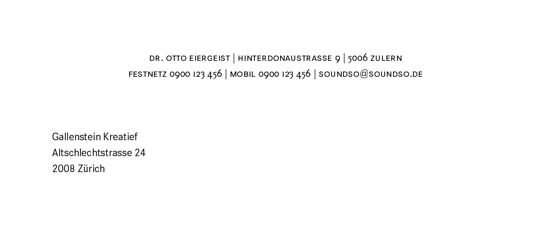
Bewerbungsschreiben für Polygraf
Hallo Miteinander!
Ich bin dabei ein Bewerbungsschreiben für eine stelle als Polygrafen aufzusetzen. Da dieser Beruf ja sehr stark mit der Schrift und die Anwendung in der Praxis verwandt ist, würde ich gerne wissen ob es irgendwelche Aspekte zu berücksichtigen gibt... ? Ich habe mir vorgestellt, dass sicher einmal die Lesbarkeit (Schriftgrad, Abstand, Zeilenlänge etc.) eine Rolle spielt und auch ein schöner Flattersatz gut ankommen wird.
Das ist jedoch nur meine Meinung als Frischling. Hat jemand damit Erfahrung oder Erfahrung mit Bewerbungsschreiben generell und könnte mir weiter helfen?
Bei der Schriftwahl bin ich mir auch noch nicht ganz sicher ob es eher eine Grotesk oder Antiqua sein sollte.
Für jegliche Hilfe wäre ich wirklich überaus dankbar!
Lieber Gruss Patrick
Hallo RobertMicheal,
Schriften hätte ich viele zur Auswahl. Da ich aber davon ausgehe, dass diejenigen, die die Bewerbungen unter die Lupe nehmen, eher mit einer alltäglichen Schrift wie z.B. der Garamond, Times New Roman oder Arial anzusprechen sind, als irgend einer Schrift aus dem Internet mit wildem stil (übertriebenes Beispiel).
also ich würde mich freuen keine systemfonts in einer bewerbung
lesen zu müssen. wenn dann höchstens georgia. ich wirds mit einer
office-schrift versuchen. fago office zum beispiel.
Ist ein Polygraf nicht ein Lügendetektor?
Ja. Es gilt aber auch Typograf+Lithograf=Polygraf 8)
Aber genau! ;)
@ RobertMichael; könntest du dir mal mein Schreiben ansehen? Ich habe es als PDF hier hochgeladen:
Die Angaben sind ein wenig verfälscht um mein Gesicht zu wahren :lol:
Wie findest du es? Für den Haupttext habe ich eine FagoCo medium benutzt und für die Überschrift eine FagoNoLF Bold. Jetzt weiss ich nicht, ob man diese, eigentlich, verschiedenen Schrifttypen in einem Brief gleich enttarnen kann oder ob ich es so durchgehen lassen kann.
Bei der Satzanordnung bin ich mir auch noch nicht sicher. Ich habe die Laufweite und den Zeilenabstand vergrössert damit es leichter zu lesen ist (war anfangs ziemlich zusammengedrückt die Schrift) und einen möchtegern Flattersatz habe ich auch noch gemacht. Ist kein schöner, da ich es schwierig fand den Text flatterig zu machen, da es zum einen sowieso nur immer ca. 3 Zeilen sind und ich mir nicht sicher bin ob ein schöner Flattersatz besser ankommt als nur ein linksbündiger Absatz.
Eine ungeordnete Liste, d.h. was mir gerade auffällt –
Linker Rand zum Satzspiegel muss deutlich ausfallen, da dein Schreiben eventuell abgeheftet wird.
Die Zeilenlänge ist viel zu groß! Lieber ein zweites Blatt riskieren.
Keine Abkürzungen, Worte ausschreiben.
Der „Flattersatz“ ist hier total unpassend, ich würde bei verminderter Zeilenlänge einen Rauhsatz bevorzugen.
Warum schreibst du Zürich groß?
Mediävalziffern – würde ich bei einer Bewerbung in diesem Stil nicht benutzen.
Achtung doppelte Leerzeichen.
Wegen der Anordnung der Elemente würde ich mich an eine Vorlage halten (DIN, gibt es etwas vergleichbares in der Schweiz?)
Formulierung: Bewerbung um eine Schnupperlehre als Polygraf
Ist das Schweizerdeutsch? Dann okay. Ansonsten eher –
Bewerbung für eine ... als Polygraf.
Hast du dein Dokument schon ausgedruckt, ist wichtig zur Beurteilung der Schriftdarstellung, der Laufweiteneinstellungen etc?
Das Kerning sieht an manchen Stellen nicht gut aus. Liegt es an deinen Einstellungen oder an der Schrift?
Ich weiß nicht, ob ich für eine Bewerbung eine Condensed-Schrift benutzen würde - vermutlich eher nicht. Und ich würde wohl auch einen etwas weniger kräftigen Schnitt verwenden.
Im Fließtext hat die führende Null bei Datumsangaben nichts verloren.
Stimmt die Position des Anschriftenfeldes? So habe ich das noch nie gesehen. Soll das für spezielle Sichtfensterumschläge passen? Wenn nicht, würde ich die Empfängeranschrift woanders hinsetzen. Wo? Naja, eigentlich links. Und dafür die Absenderadresse vielleicht einzeilig, dann ist mehr Platz nach unten.
Vor dem "es sich herauskristallisiert" fehlt doch was?
Dein Name muß nicht mehr unter dem Brief stehen, nur die Unterschrift.
Du möchtest nicht "gerne diesem Beruf" erlernen, sondern "diesen", und Du möchtest diesen Satz auch mit einem Punkt abschließen (und ein Komma hinter die Anrede am Briefanfang).
Was ist denn eigentlich eine "Freiberufler Baustelle"?
Die Abstände zwischen den Absätzen könnten kleiner sein, es muß hier doch nicht Register gehalten werden.
Du arbeite am Computer "mit Programmen wie Photoshop", nicht "mit den Programmen wie Photoshop".
Ich finde übrigens, Du hast diese Bewerbung sehr gut formuliert.[/url]
- die Anschrift würde ich nach links setzen und das Datum ganz nach rechts
- hinter "Sehr geehrte Damen und Herren" setzt man üblicherweise ein Komma und schreibt dann klein weiter
(wobei es natürlich sein kann, dass es in der Schweiz so üblich ist, wie Du es in Deinem Brief gemacht hast)
Ja, das ist so. Wir haben tatsächlich Fenstercouverts mit Fenster links oder rechts. Anhand des gewählten Fensters wird dann eben der Brief gestaltet. Allerdings beschneidet die Schweizer Post den Gestaltungsspielraum auf den Couverts dermassen, dass es sich schon fast nicht lohnt, sich darüber Gedanken zu machen. Ich frage mich, wie lange es noch dauert, bis Strafporti auf handadressierte Briefe entfallen.
Anhand des gewählten Fensters wird dann eben der Brief gestaltet..
Wähle einfach einen Umschlag mit dem Fenster auf der linken Seite, dann sieht's innen besser aus.